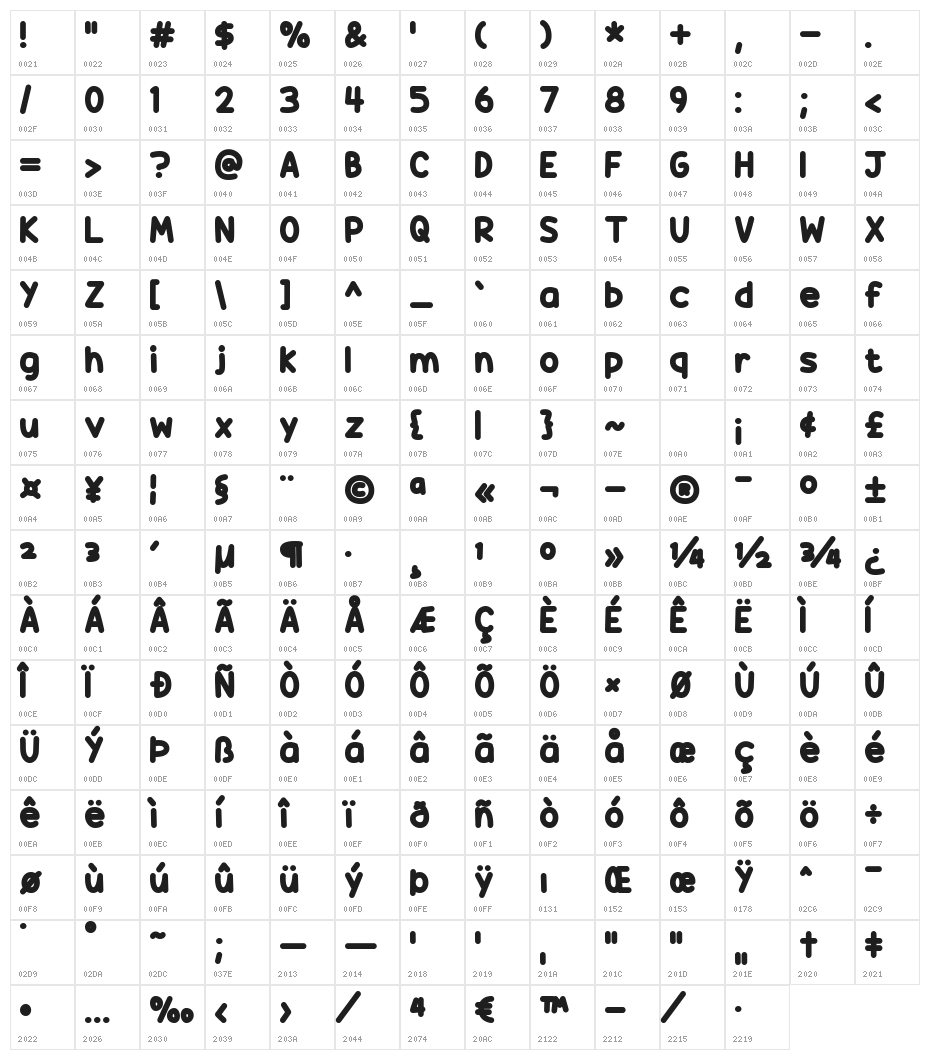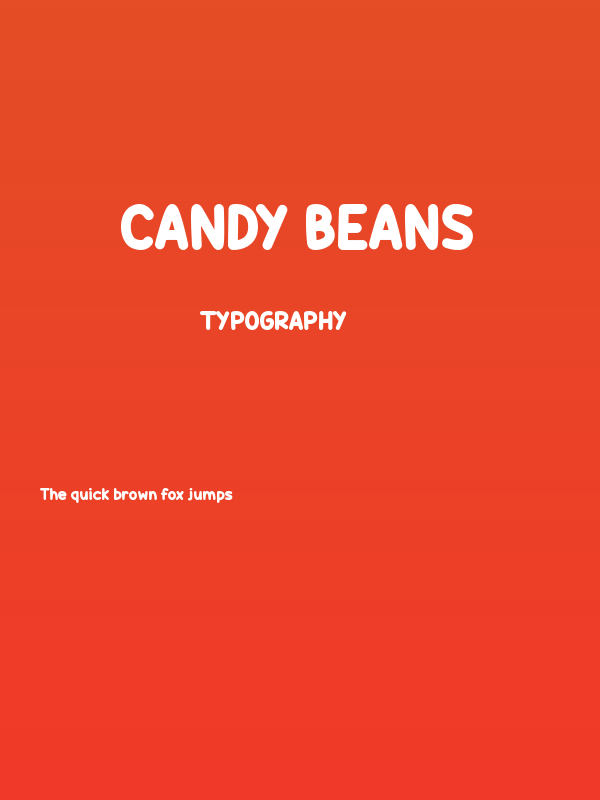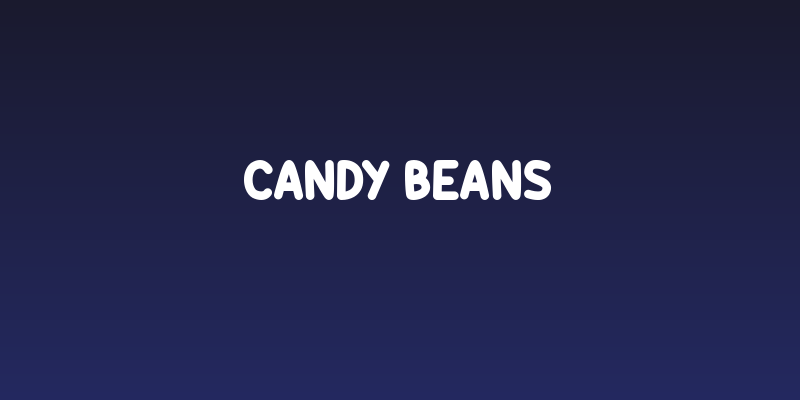
Candy Beans Font
| Stile generale | Playful, Whimsical |
| Progetti proposti | Ideal for children's books, playful branding, greeting cards, and creative posters. |